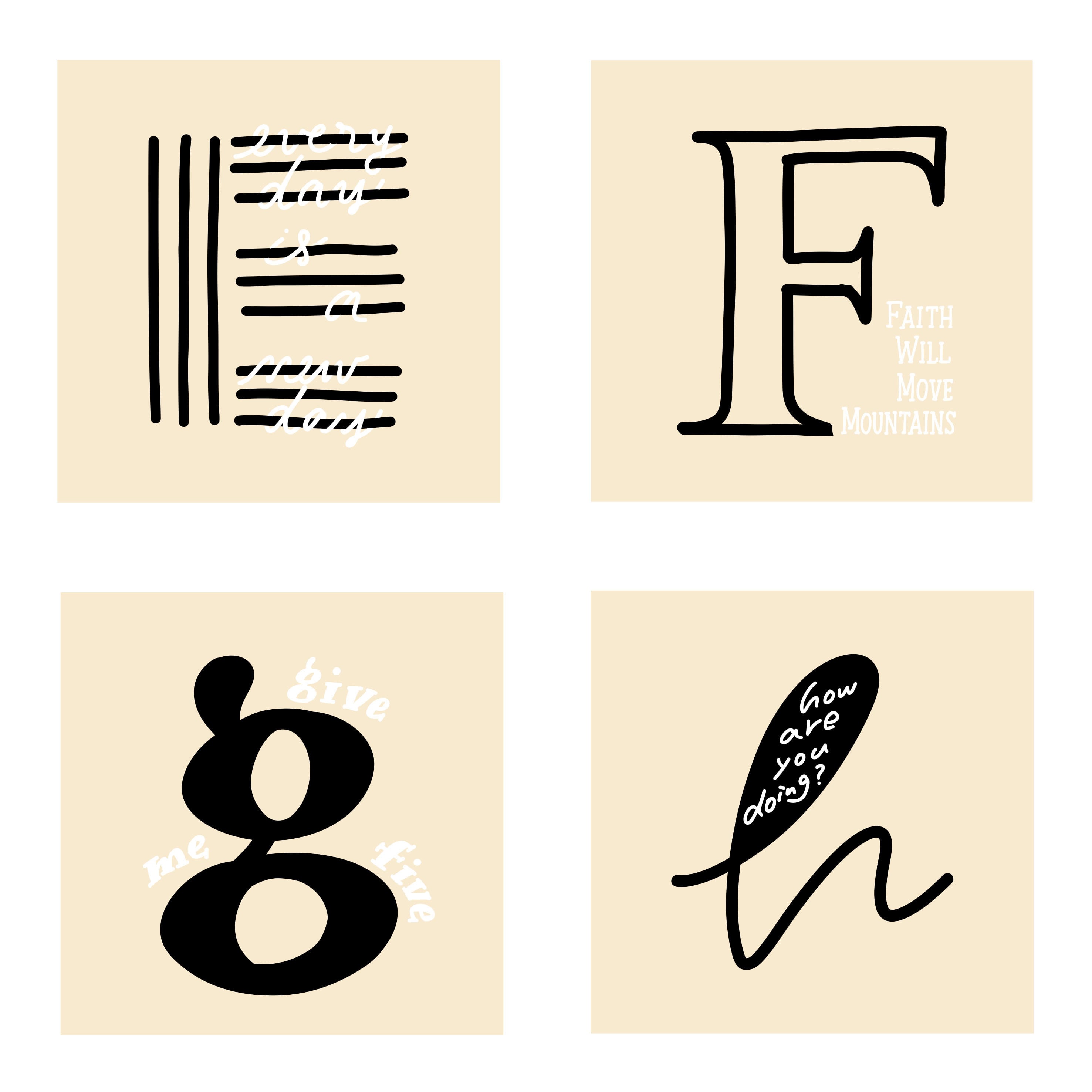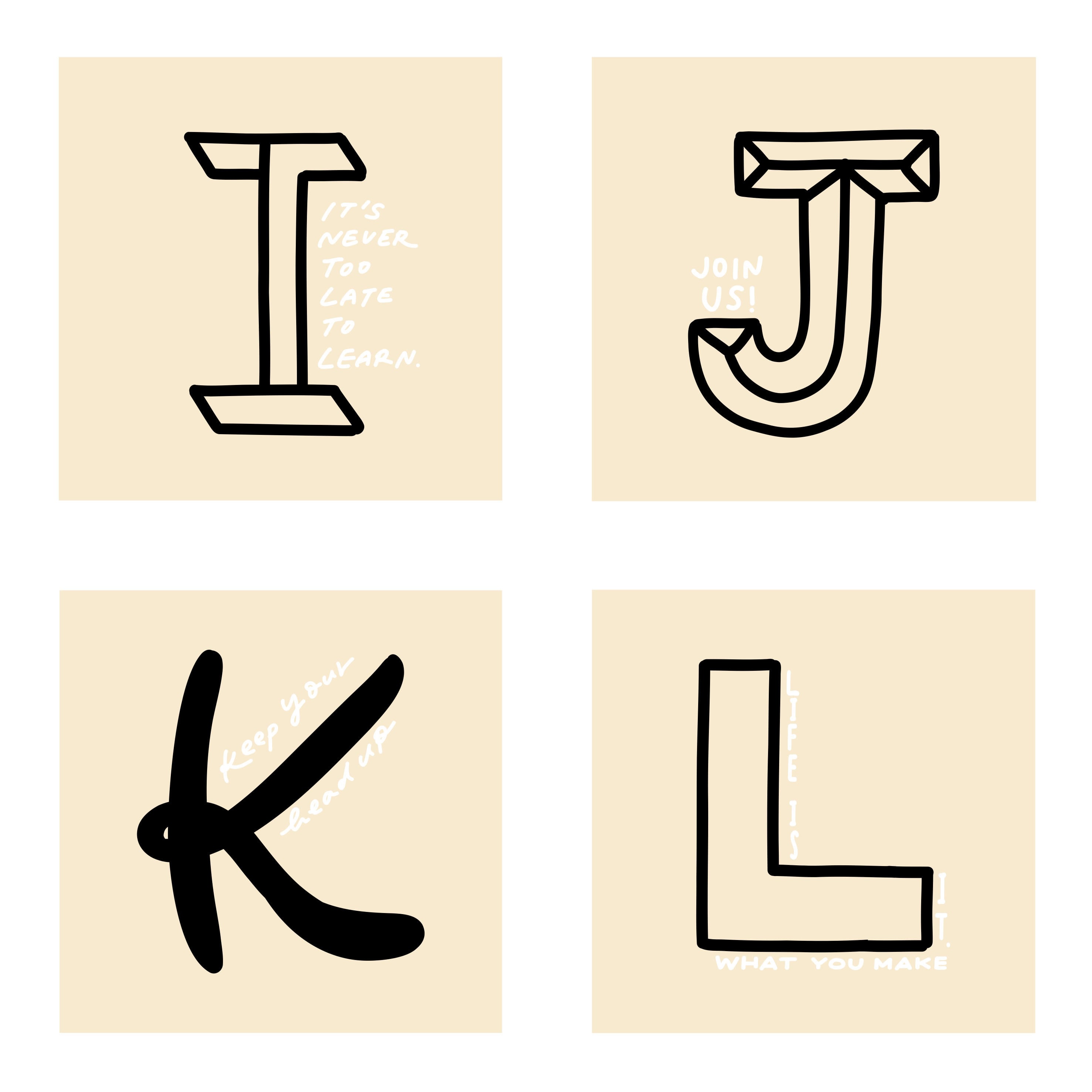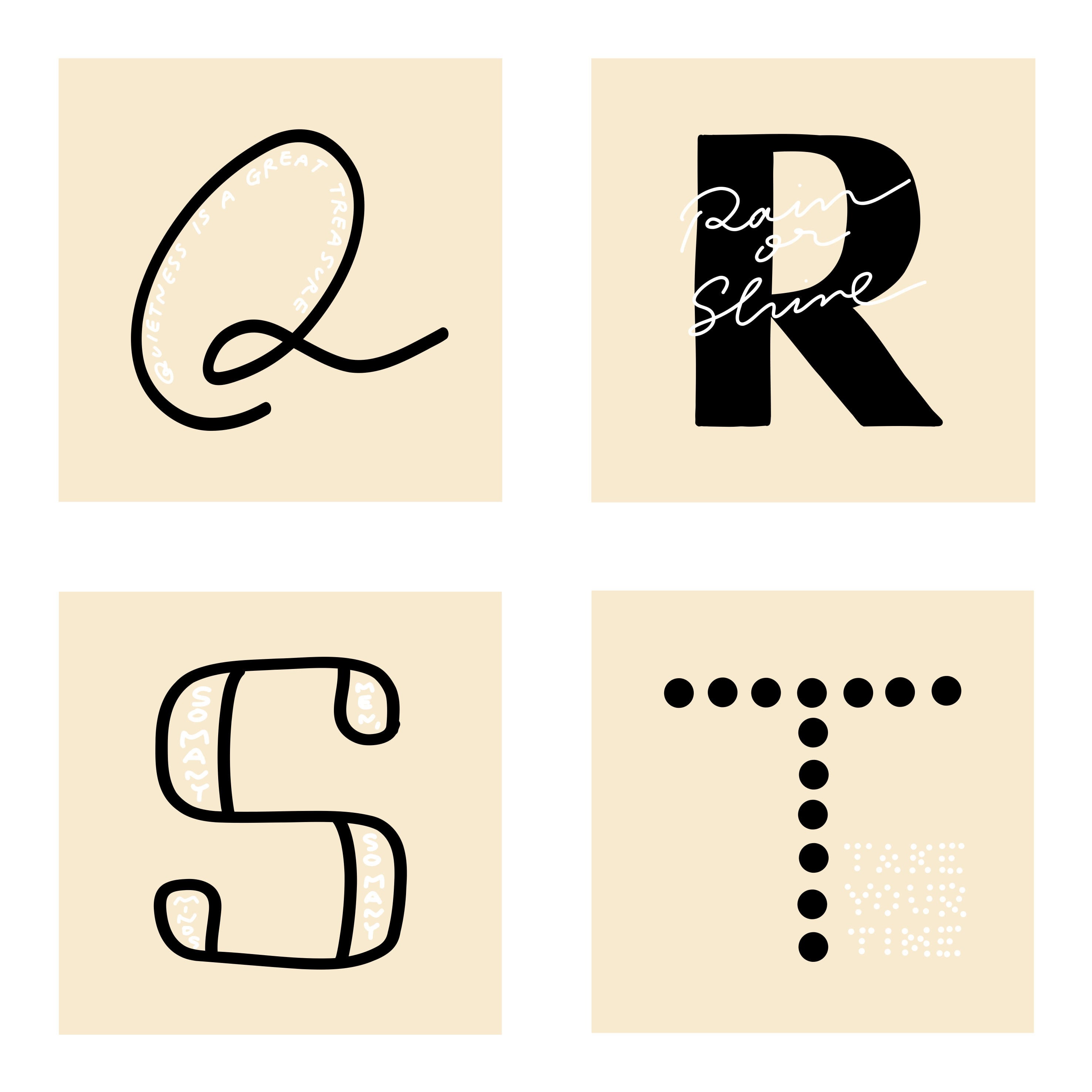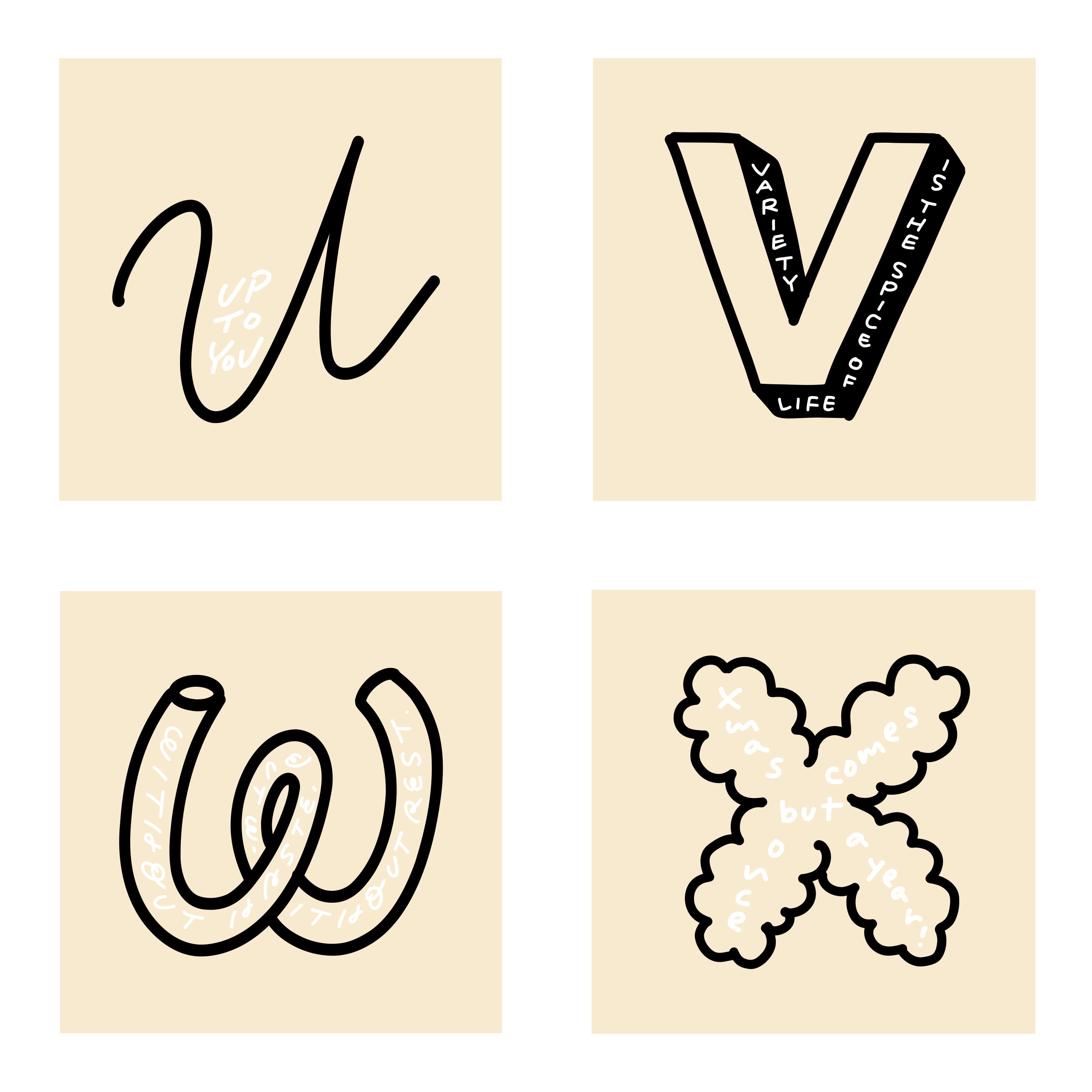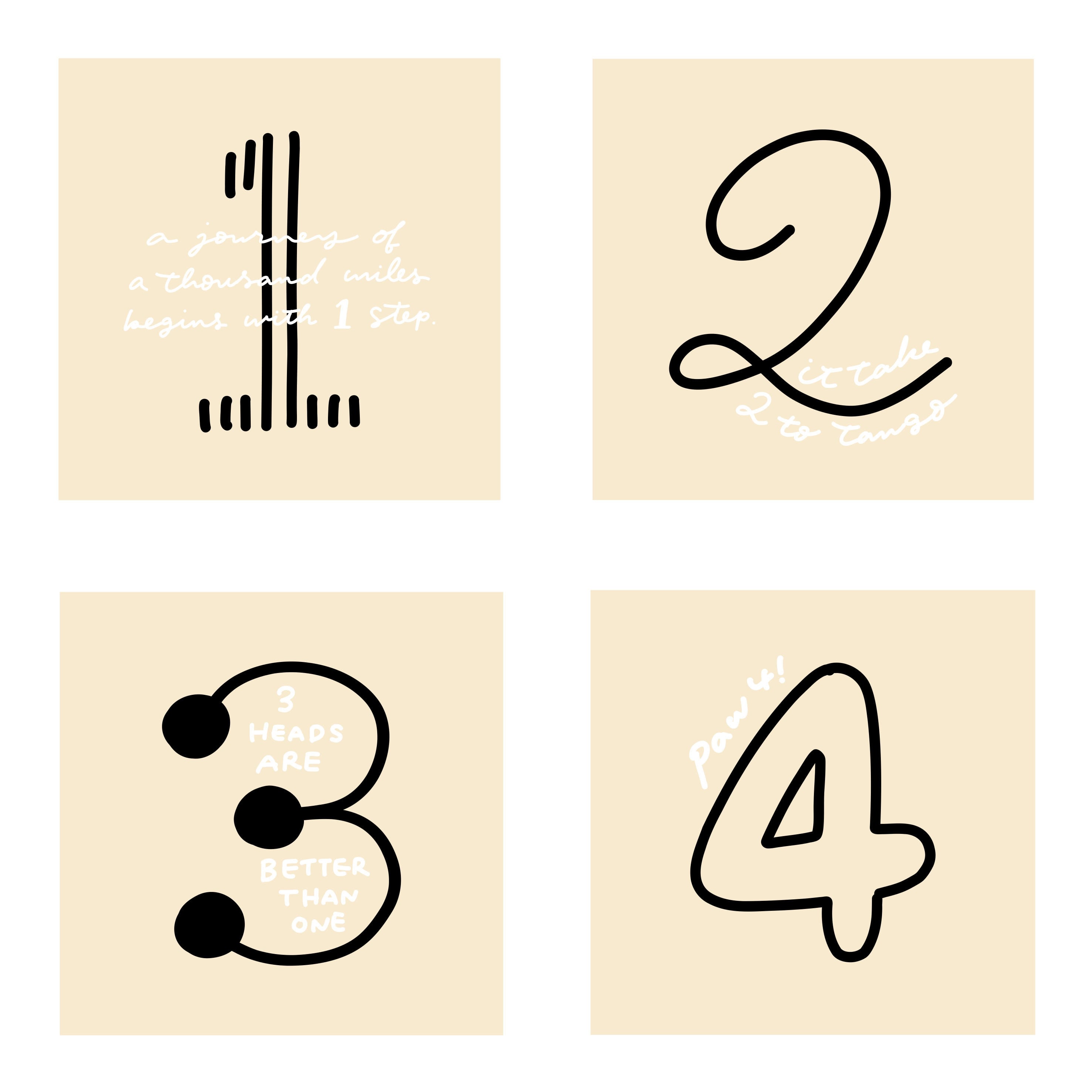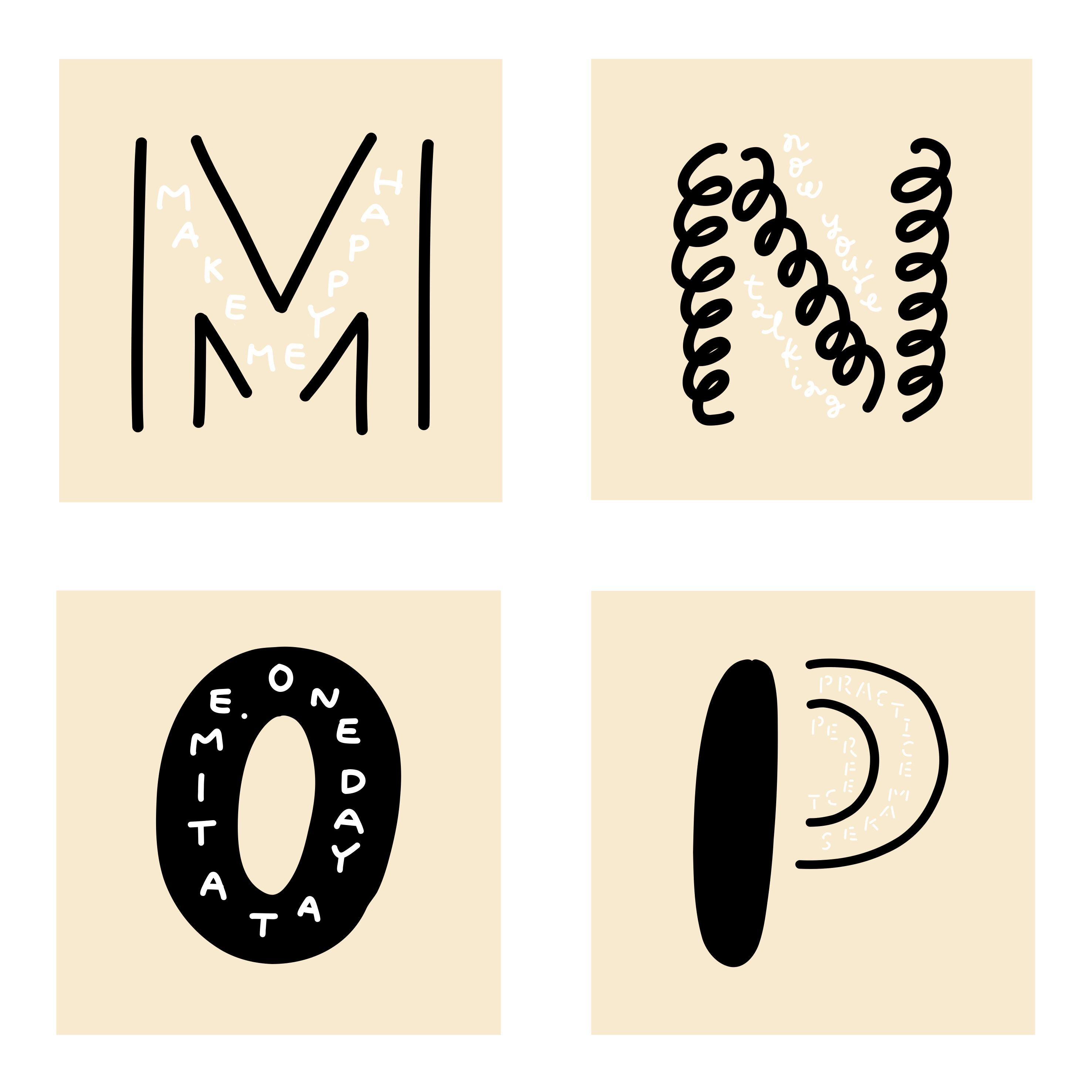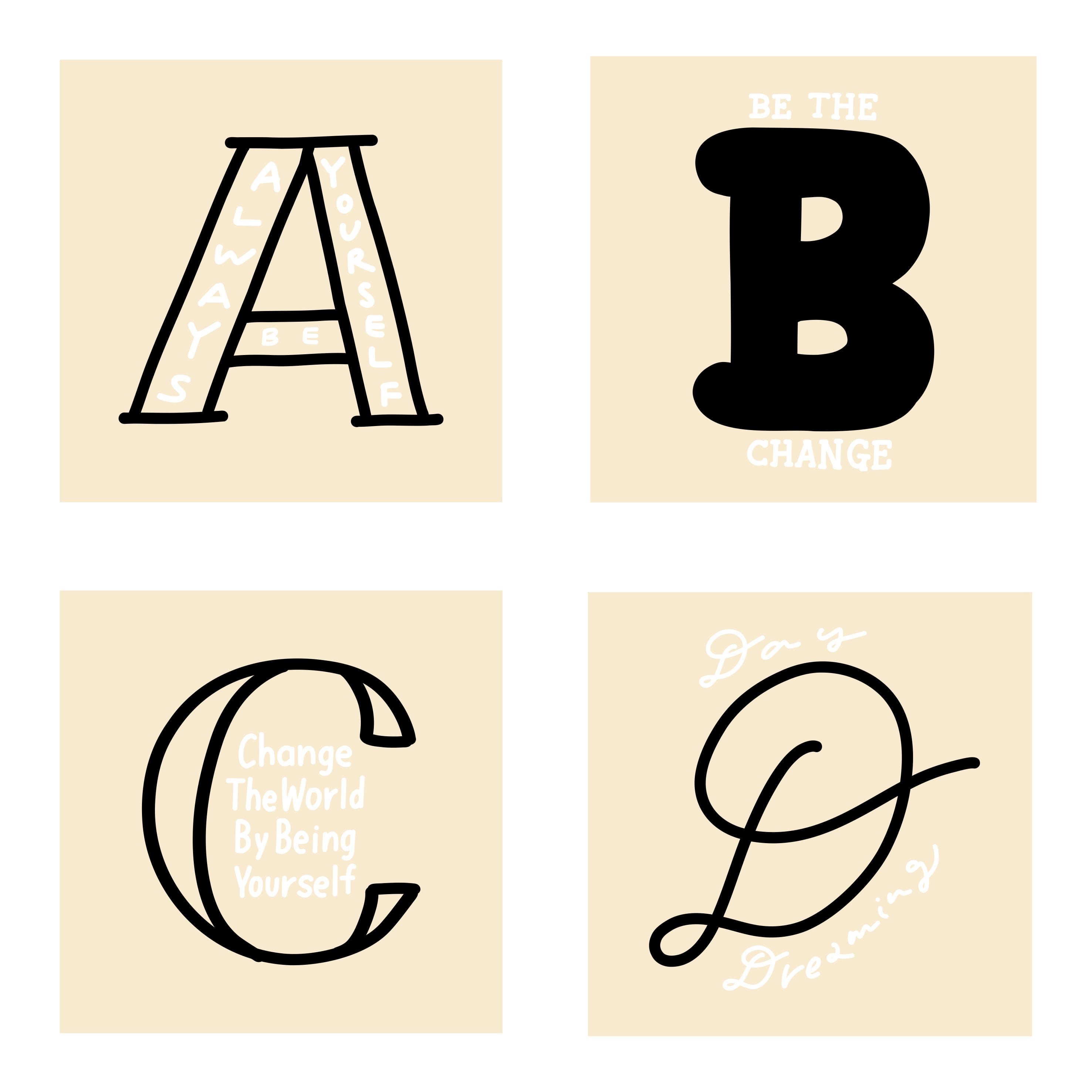
ALPHABET WORLD(A〜Z、1〜4)
ALPHABET WORLD
アルファベット26字と1〜4、全部で30種類!
アルファベットをメインに、そのアルファベットから始まるフレーズが控えめに入っています。
(1〜4はフレーズの中に数字で入っています)
Always be yourself/いつもあなたらしく
Be the change. /変化になれ
Change the world by being yourself. /自分を変えることで世界を変えよう
Day dreaming /空想にふける
Every day is a new day/とにかく、新しい毎日なんだ
Faith will move mountains. /信念は山を動かす
Give me five!! /ハイタッチ!
How are you doing? /調子どう?
It is never too late to learn. /学ぶのに遅すぎることはない
Join us /一緒にどう?
Keep your head up/うつむかず、頭を上げて。
Life is what you make it. /人生は自分でつくるもの
Make me happy /私を幸せにするもの
Now you’re talking / そうこなくっちゃ!
One day at a time /一歩ずつ
Practice makes perfect /継続は力なり
Quietness is a great treasure/静穏は大きな宝物である
Rain or shine/どんなことがあっても必ずやる
So many men, so many minds /十人十色
Take your time/ゆっくりでいいよ
Up to you /キミ次第
Variety is the spice of life /多様性は人生のスパイス
Without haste, but without rest/急がずに、でも休まずにね
Xmas comes but once a year /クリスマスは年に一度しか来ない
You made my day /最高の一日になった
Zest for life/生きる力
A JOURNEY OF A THOUSAND MILES BEGINS WITH 1 STEP/千里の道も一歩から
It takes 2 to tango /タンゴを踊るには二人必要
3 heads are better than one /三人寄れば文殊の知恵
Paw 4 /(イヌとネコの)ハイタッチ!